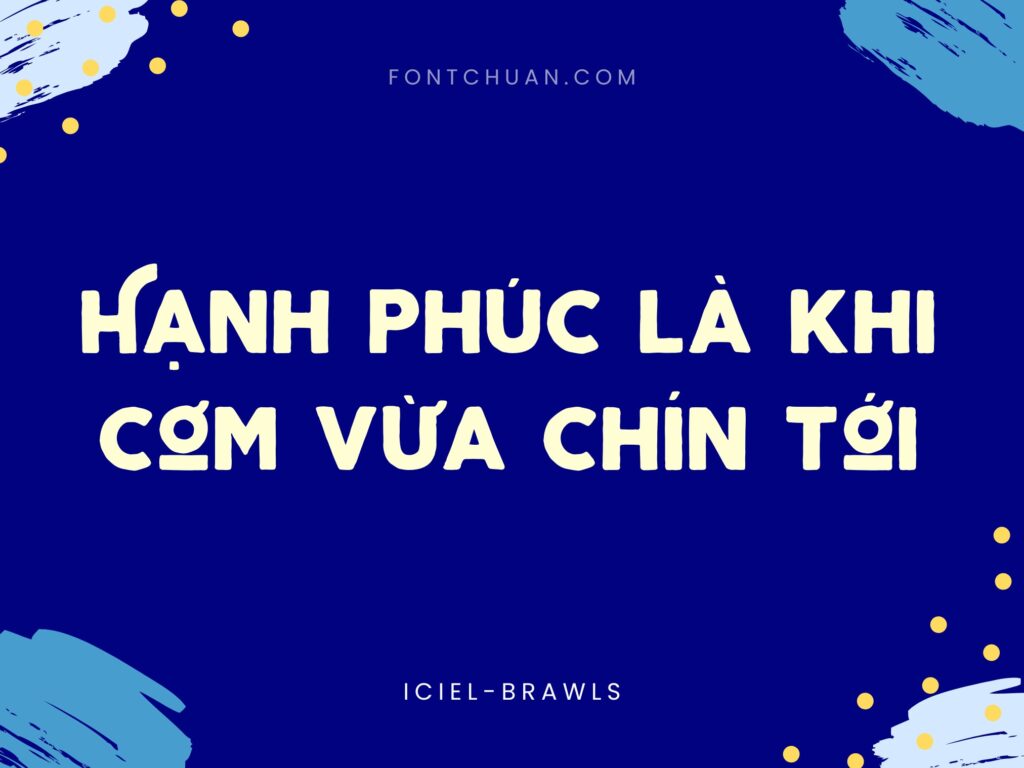
Font iCiel Brawls Việt Hóa
Tác giả Font: Heybing Supply Co
Việt hóa bởi: Iciel
Brawls là một font chữ mang phong cách hiện đại với thiết kế độc đáo, các ký tự được tạo hình góc cạnh và mạnh mẽ, tạo nên sự chuyên nghiệp và thu hút cho các dự án thiết kế. Font này được thiết kế bởi El Gato en la Luna và đã được Iciel Việt hóa, hỗ trợ đầy đủ tiếng Việt cùng hơn 200 ngôn ngữ khác. Phiên bản Brawls Việt hóa đã được thành viên Font Chuẩn sưu tầm và đăng tải, mang đến sự lựa chọn đa dạng cho các nhà thiết kế.
Về đặc điểm thiết kế, Brawls sở hữu các ký tự in hoa với đường nét đậm và góc cạnh, tạo nên sự mạnh mẽ và nổi bật. Font này rất phù hợp cho các thiết kế như tiêu đề, poster, logo, bao bì sản phẩm và các dự án cần sự cá tính và hiện đại. Ngoài ra, Brawls cũng là lựa chọn lý tưởng cho các ngành nghề như quảng cáo, công nghệ, giáo dục và bất động sản, mang lại phong cách chuyên nghiệp và thu hút. Font này cũng thích hợp để sử dụng trong các sự kiện như lễ hội, sinh nhật và các dịp đặc biệt khác.